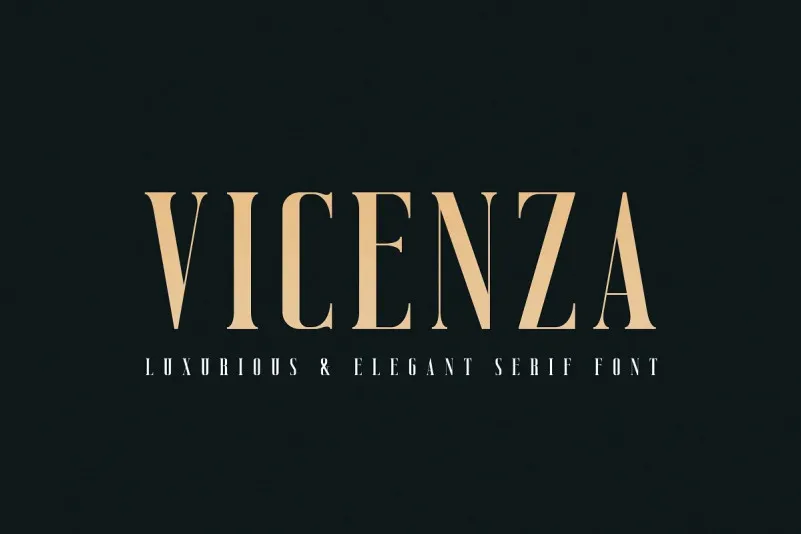
Vicenza Font
Vicenza Font é uma elegante e sofisticada família de tipo serif que surge da criativa Almarkha Type. Especialmente adequado para projetos de branding pessoal, essa família de fontes regular e itálica inspira-se no logo minimalista famoso. Com 2 estilos distintos, Vicenza é perfeita para a criação de modelos, brochuras, vídeos, publicidade, logotipia e muito mais. Seja você um designer gráfico proeminente ou iniciante buscando um estilo arquitetônico elegante que seja fácil de usar e interage com uma variedade de materiais digitais, Vicenza tem o potencial para revolucionar sua abordagem ao criar conteúdo visual. Em seu pacote completo, você encontrará um conjunto sólido de fontes que podem ser usadas em diversas aplicações visuais sem preocupações desnecessárias. Este é mais do que apenas uma fonte; é um passo em direção a uma identidade visual única e profissional.